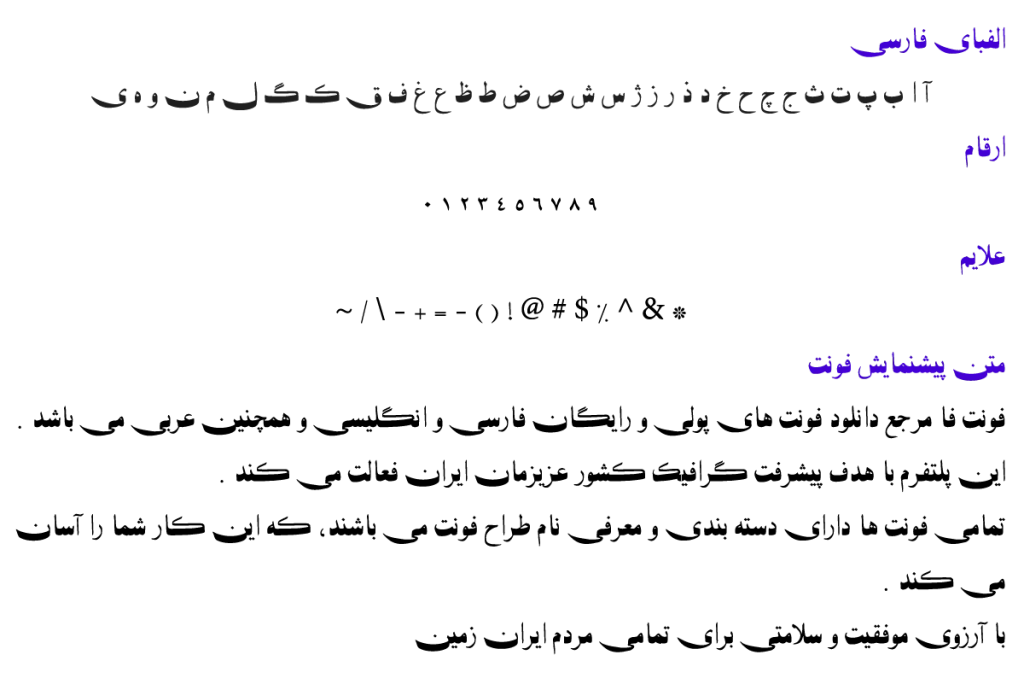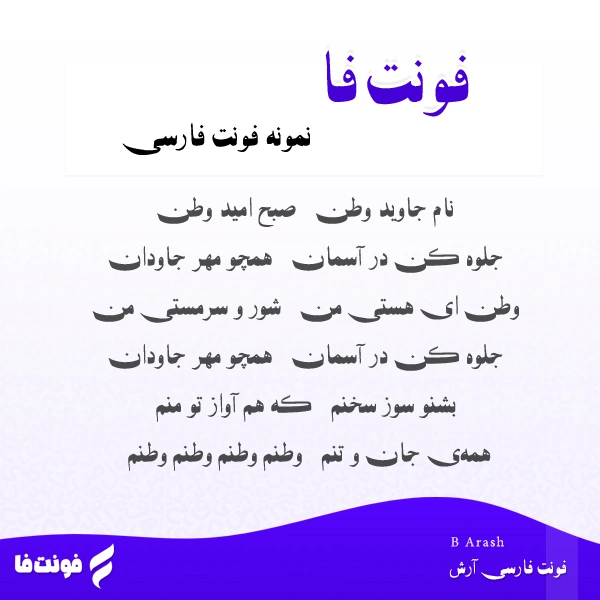
فونت فارسی آرش – B Arash
سال ساخت فونت: 1379
مجموعه فونت: فونت سری B
طراح فونت: برنا رایانه نوع فونت: فونت فانتزی
پیشنمایش فونت بی آرش
توضیحات و معرفی فونت آرش
فونت فارسی آرش ( B Arash ) از مجموعه فونت های سری B می باشد، و نیز نوع فونت فانتزی می باشد.
فونت خوشگل مربوط توسط برنا رایانه در سال 1379 طراحی و ساخته شده است.
و نیز فونت B Arash در یک وزن پر رنگ است.
در عکس زیر، پیش نمایشی از این تایپ فیس را می بینید که با آن شعری کهن درباره ایران نوشته شده است.